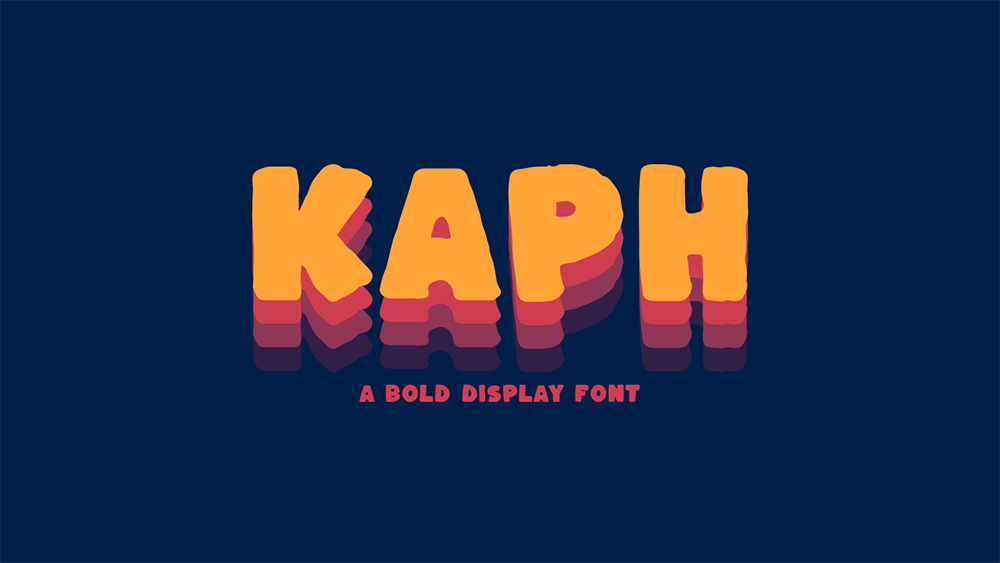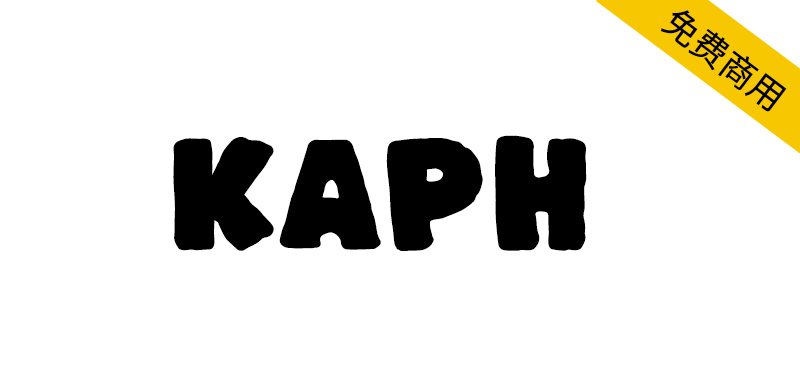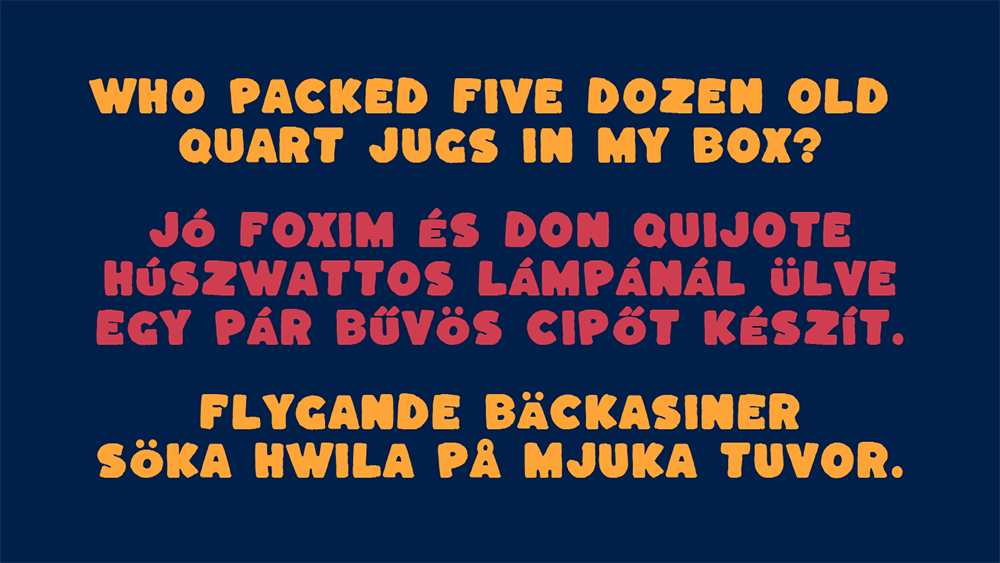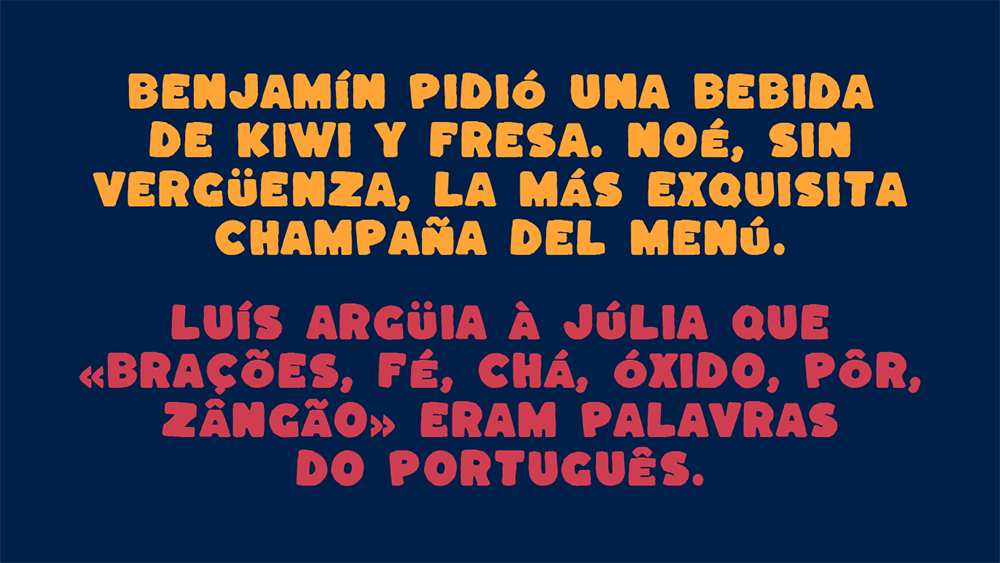
【Kaph】手写可爱风格免费英文字体,2种样式和443个字形
Kaph是一款根据SIL OFL协议发布的免费英文字体,手写风格, 2 种样式(Regular、Italic)和 443 个字形。
支持 38 种语言:阿尔巴尼亚语、罗马尼亚语、阿斯图里亚斯语、布列塔尼语、加泰罗尼亚语、捷克语、丹麦语、荷兰语、英语、爱沙尼亚语、芬兰语、法语、加告兹语、德语、匈牙利语、伊博语、印度尼西亚语、爱尔兰语、意大利语、拉丁语、拉脱维亚语、立陶宛语、马耳他语、挪威语、波兰语、葡萄牙语、苏格兰盖尔语、斯洛伐克语、斯洛文尼亚语、西班牙语、瑞典语、他加禄语、瓦尔瑟德语、威尔士语、西弗里斯兰语、祖鲁语。